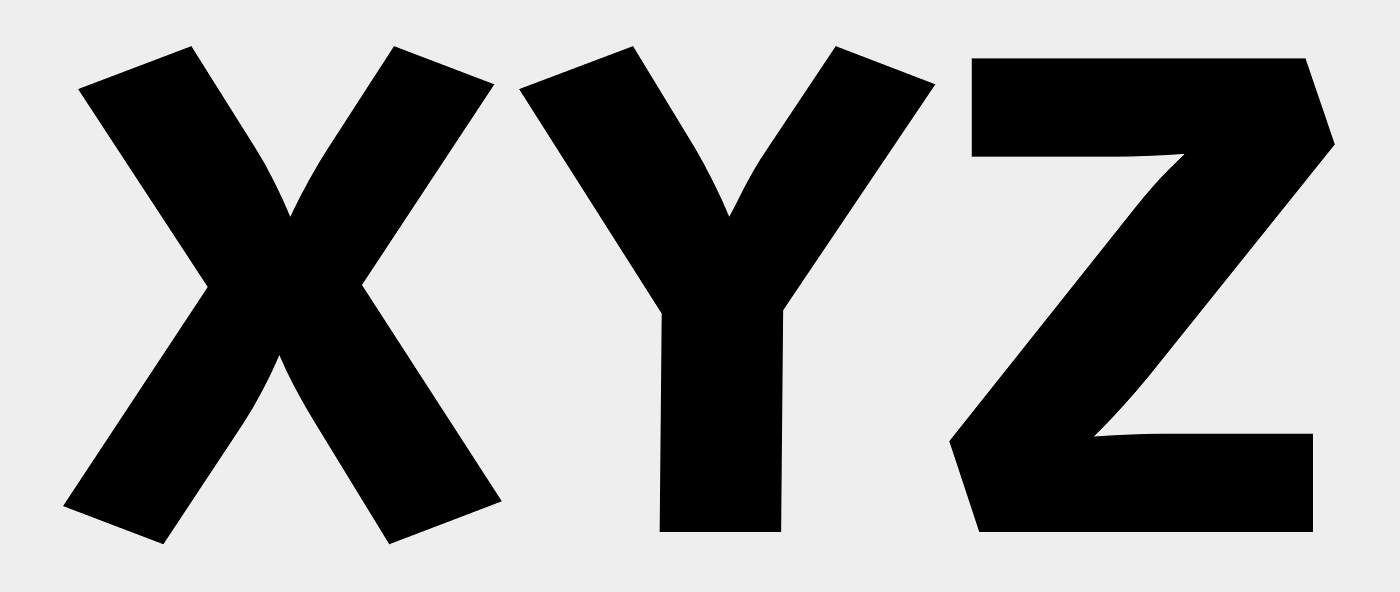
Schriftart ähnlich Skia gesucht (bold, schönes X...)
Ich habe zwar Skia installiert. Aber aus irgendeinem Grund kann ich nicht die bold Versionen aufrufen und in dem Programm verwenden wo ich es verwenden kann. Außerdem vermute ich, dass die bold Versionen sowieso zu dünn sind. Deshalb suche ich eine (free) Schriftart, die möglichst modern, ein bischen originell, aussieht, wahrscheinlich serifenlos, die es auch in sehr fett (heavy, bold..) gibt und vor allem das X ist wichtig. Heißt, es sollte vom Grundkonzept so gestaltet sein wie bei der Skia, dass also die obersten Begrenzungslinien des X nicht horizontal verlaufen, sondern... ja, wie beschreiben, also so, dass das X eher wie ein Kreuz aussieht. Ideen?
Hab ich schon, hab noch nichts gefunden, und dauert sehr lange alle einzeln nachzuschauen. Vielleicht kennt ja jemand aus dem Kopf. Es geht halt vor allem darum, dass die "Endkanten" bei den Buchstaben X, Y, k usw.so sind als ob die Schrift aus kleinen Balben zusammengesetzt sind, so wie es bei Skia halt ist, aber Skia ist zu dünn...
Eventuell käme die London von François Bruel in Frage? Sie hat zumindest diese Buchstabenformen. Und es gibt eine Fette… Ansonsten haben zumindest das Fonthörnchen und die OpenFontLibrary in ihren als serifenlos markierten Schriften nichts passendes…
Schau dir mal hier die Alternativen zur Skia an:
Also, ich sehe da 30 Alternativen und um nach den genannten Maßstäben zu sortieren  oder auszuklammern dauert ... ’ne Minute :-?